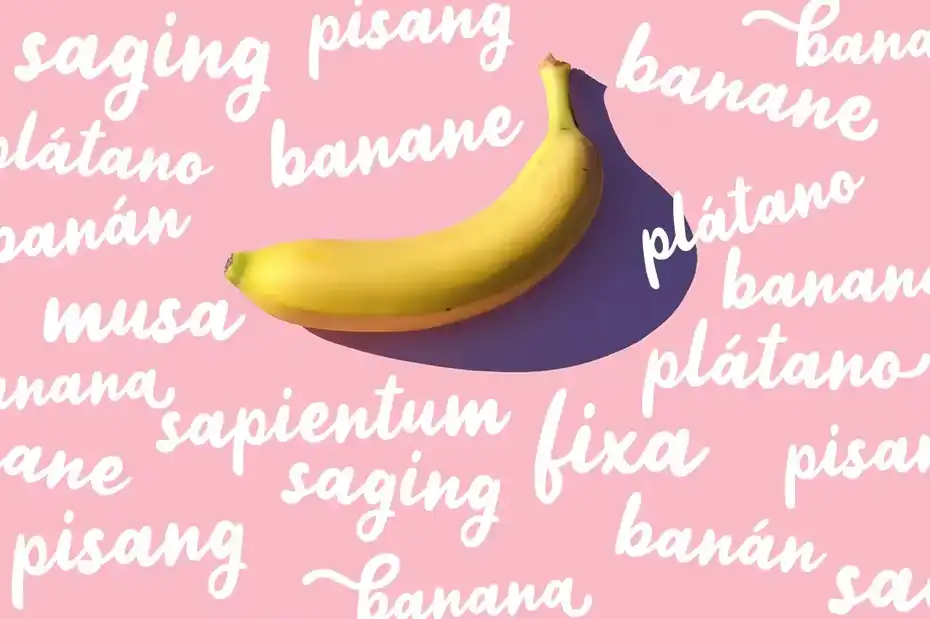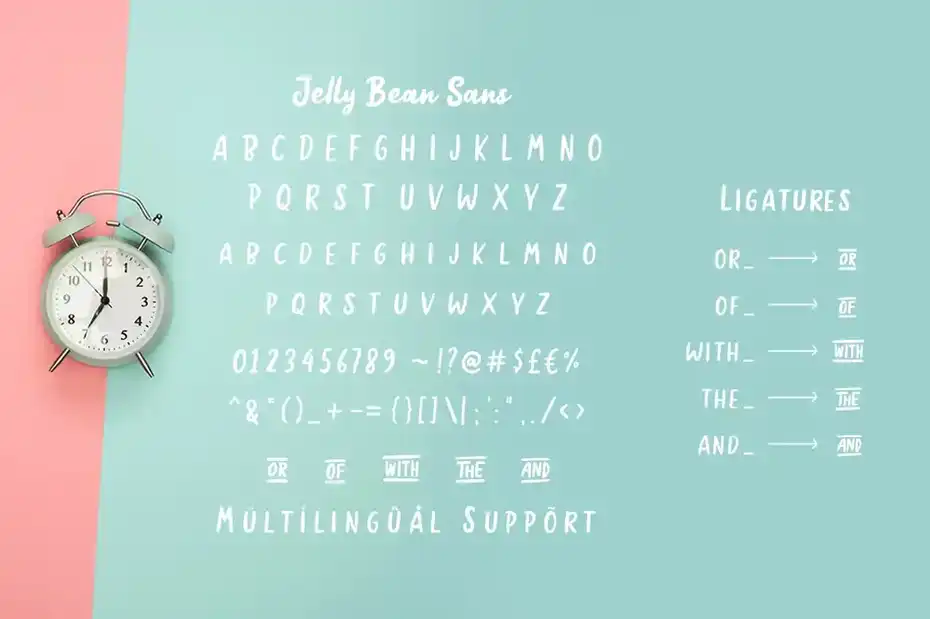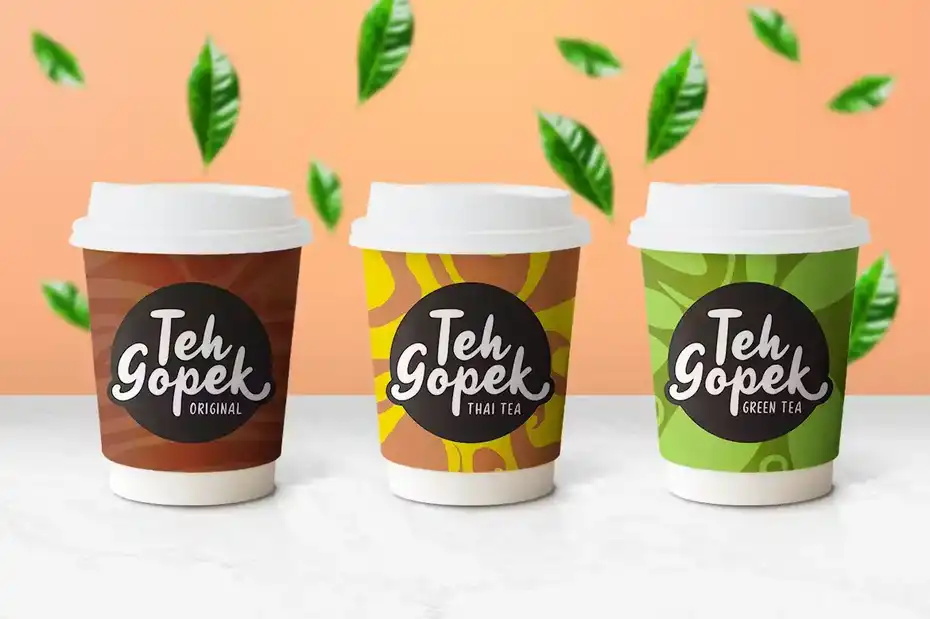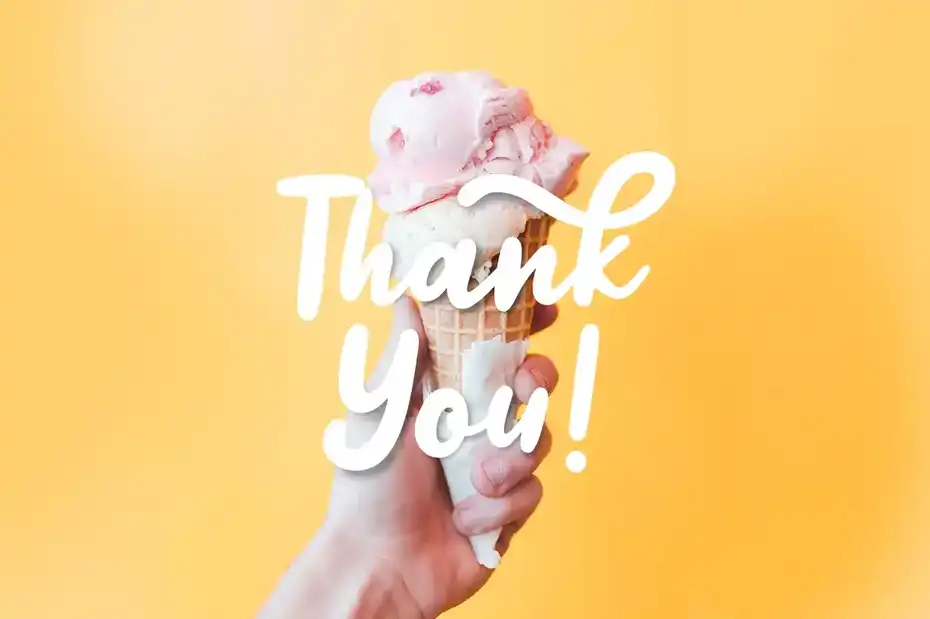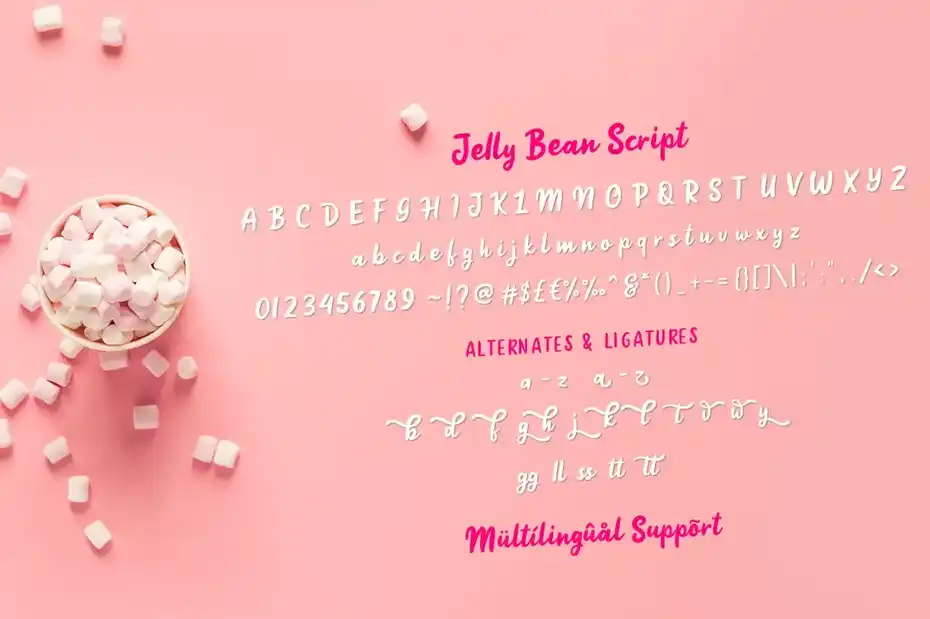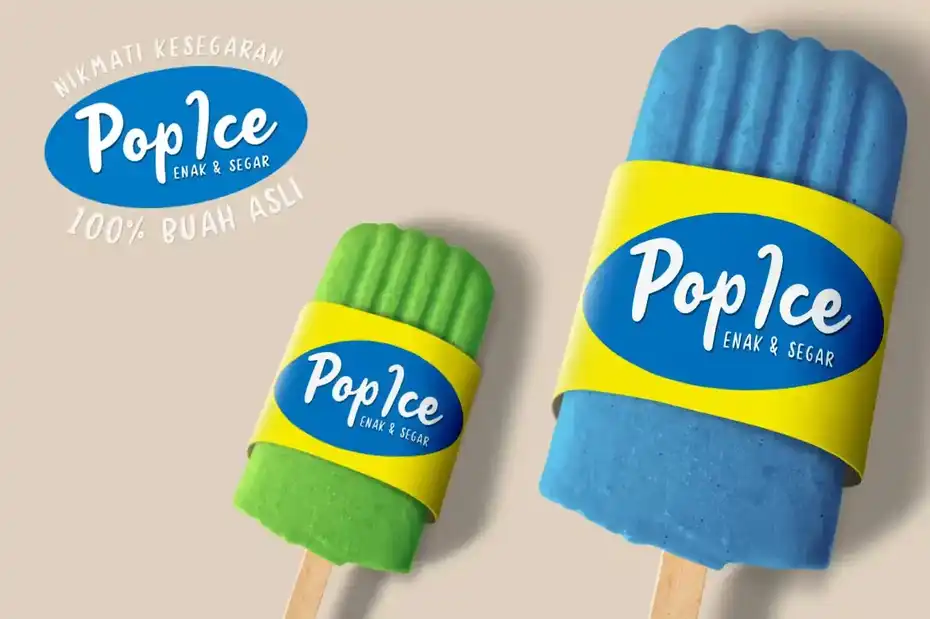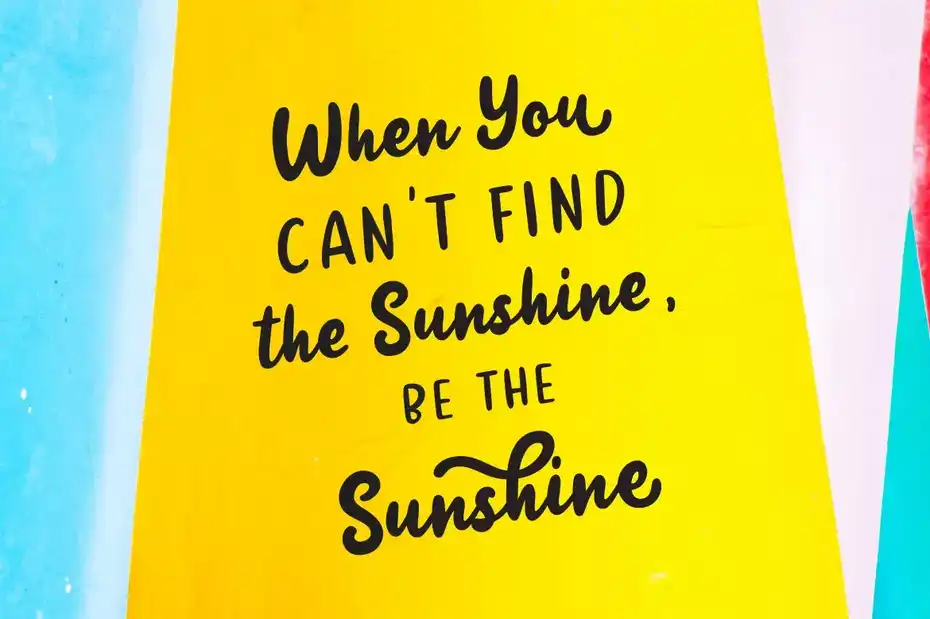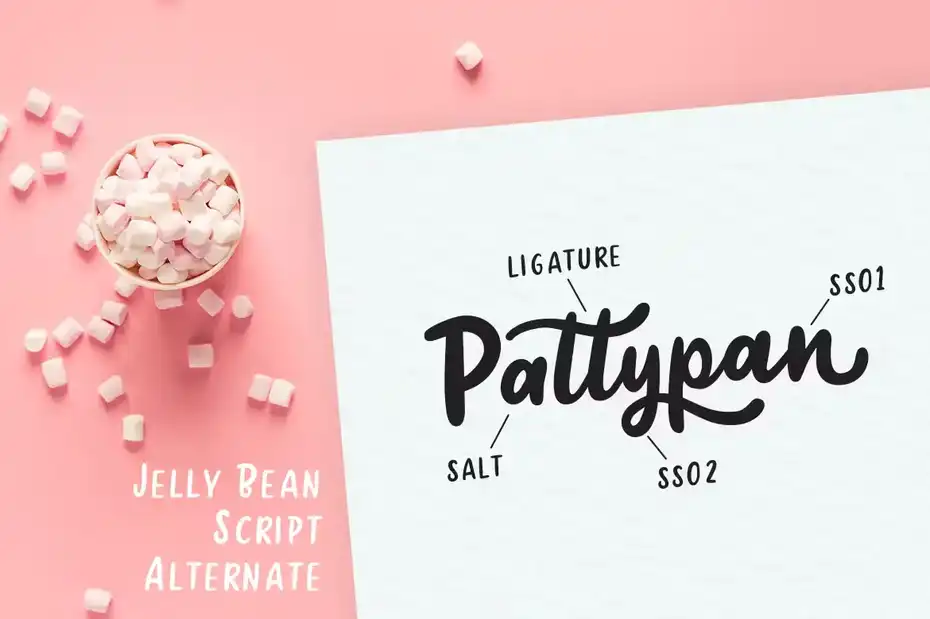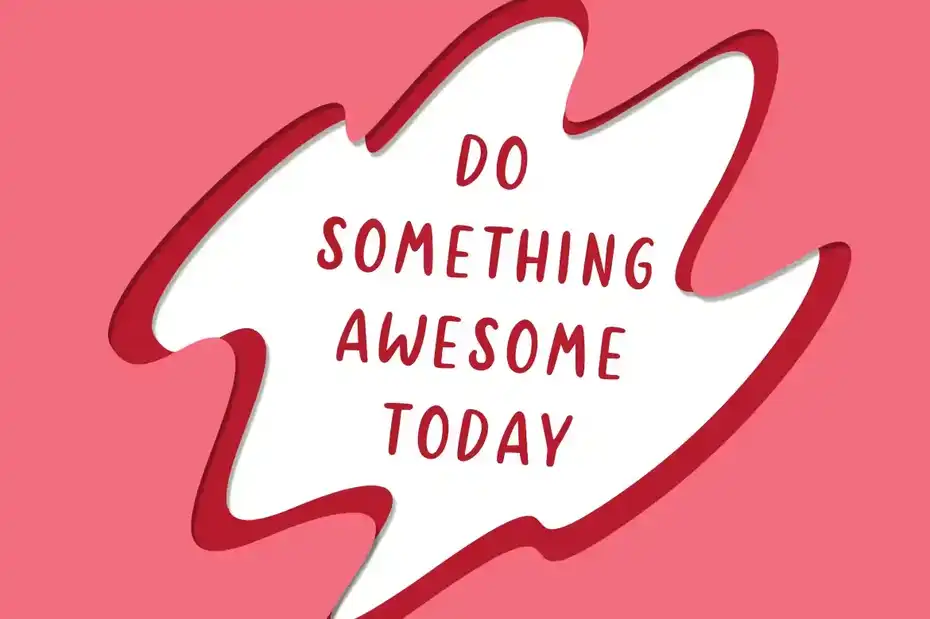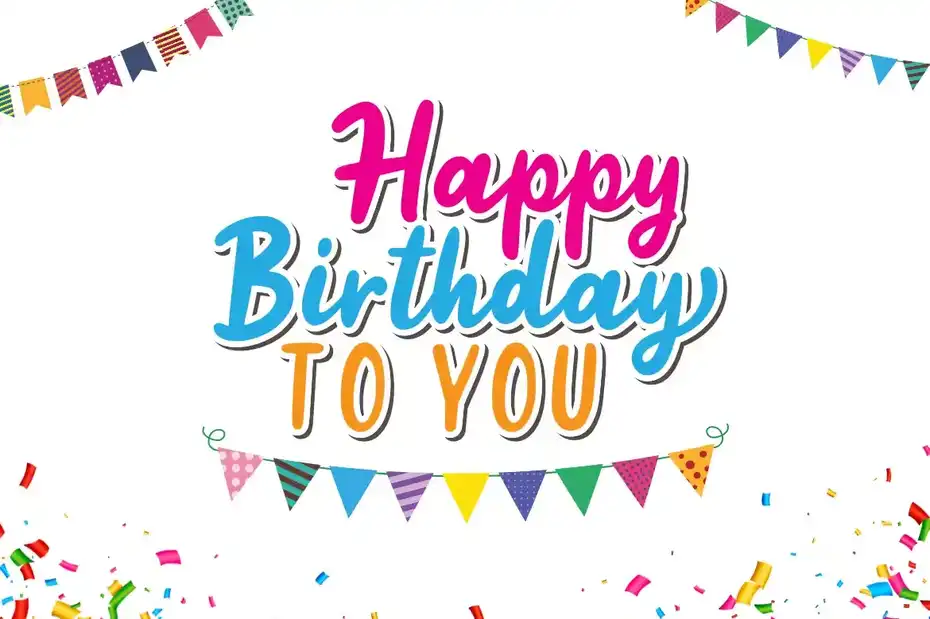
فونت انگلیسی دست نویس Jellly Bean Script & Sans Fun Font : این مجموعه شامل یک فونت انگلیسی دست نویس است که برای لوگو، تیشرت های بچه گانه، کارت دعوت تولد، جلد کتاب، نقل قول ها، بسته بندی و غیره مناسب میباشد.
• سبک: Sans-Serif